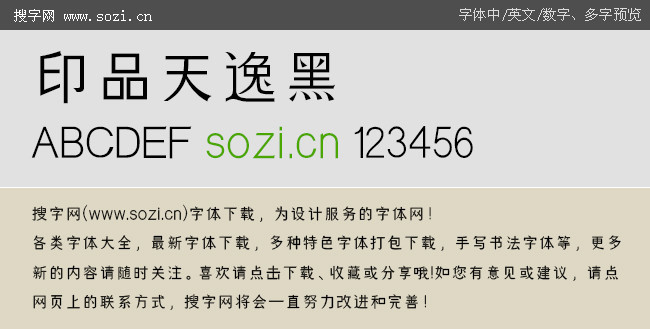
印品天逸黑
搜字網(wǎng)給大家提供一款印品天逸黑中文字體下載,印品天逸黑字形筆畫整齊劃一、簡潔大方,橫豎筆畫基本上保持一致,個性鮮明,引人注目。字體結(jié)構(gòu)嚴(yán)謹(jǐn)端莊,字形飽滿,硬朗的筆劃賦予其力量感,整體風(fēng)格剛勁有力而又不失俊儒之風(fēng)。適用于海報設(shè)計、包裝設(shè)計、商業(yè)廣告等廣告設(shè)計。